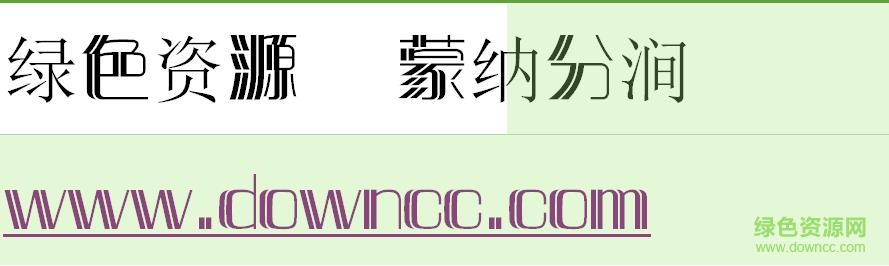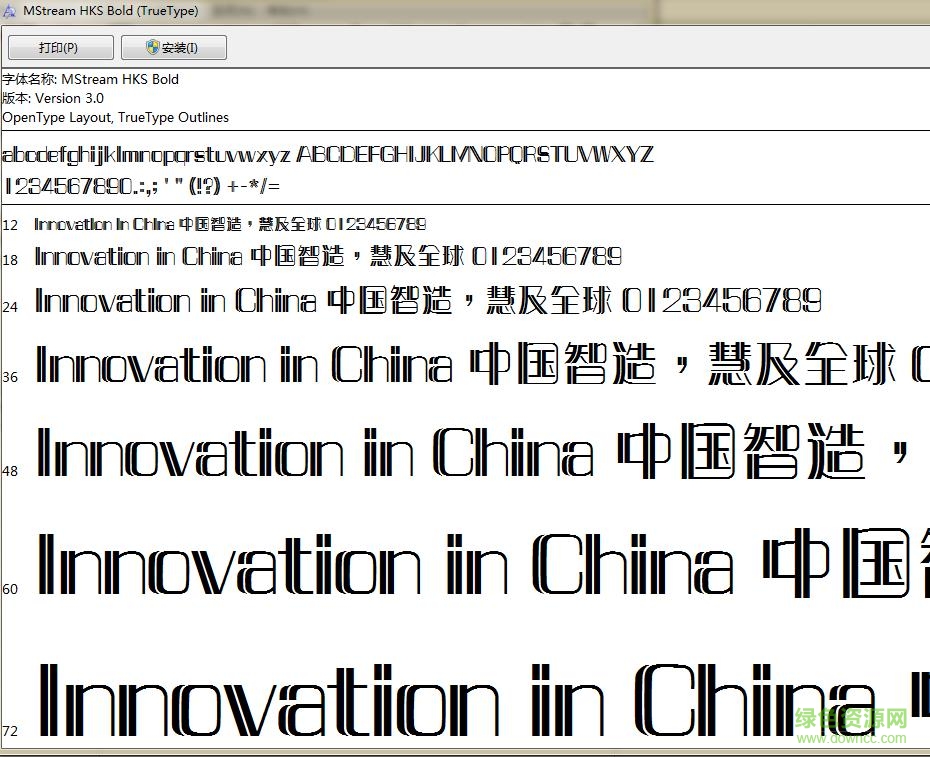
蒙納分澗體ttf在蒙納字體中擁有十分獨(dú)特的地位,這款字體中的每一個字都能夠?qū)崿F(xiàn)雙重視覺體驗(yàn),讓你感受到分澗顯示的趣味效果,這樣的字體運(yùn)用到一些媒體制作行業(yè)中將取得十分不錯的視覺效果!
蒙納分澗體在不斷的發(fā)展演化中逐漸廣為用戶喜愛,如果在手機(jī)上顯示的化就能夠讓你的小伙伴感受不同以往的字體顯示效果,這對一些字體癌用戶們十分受用!